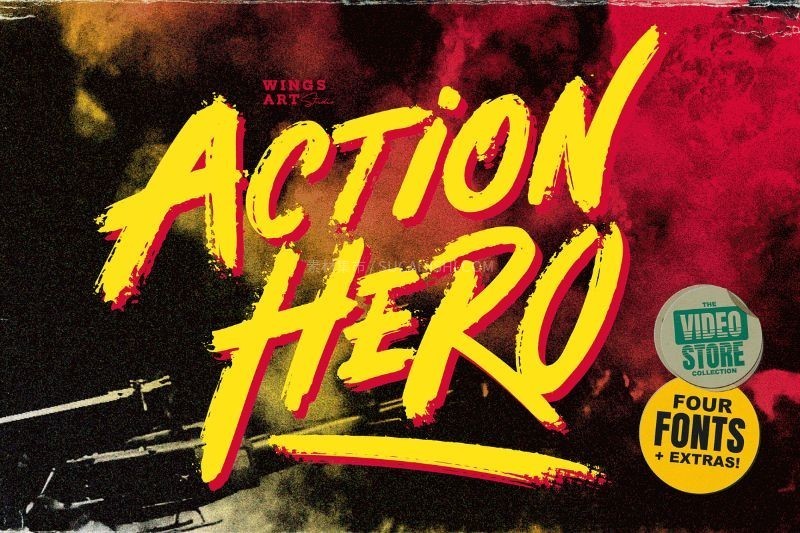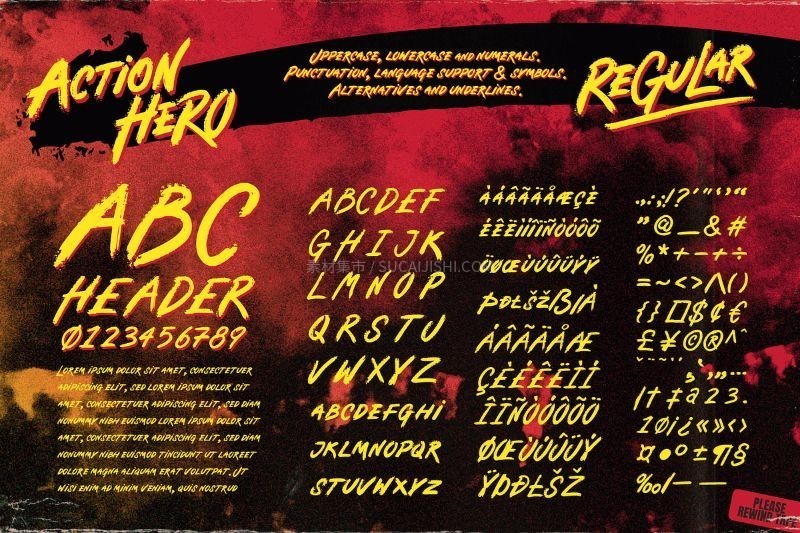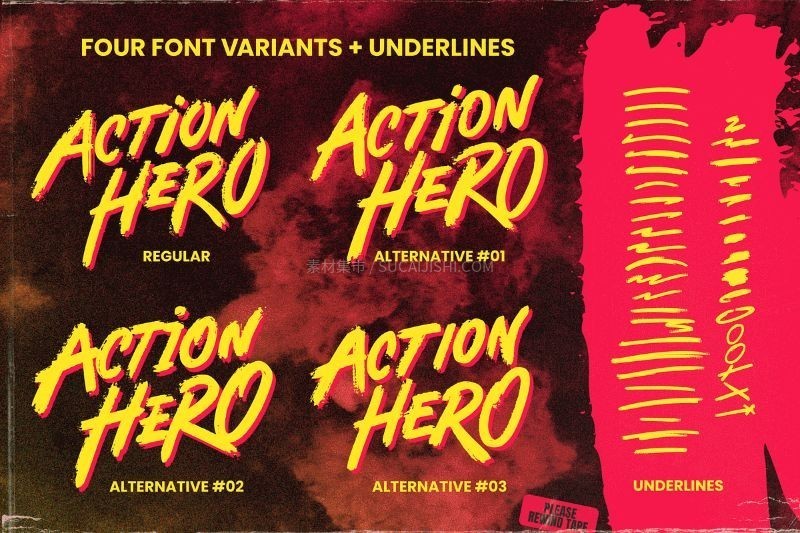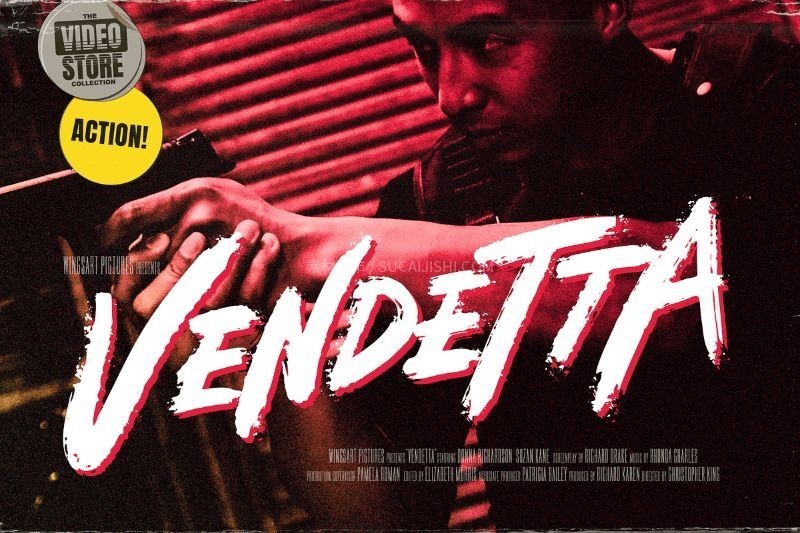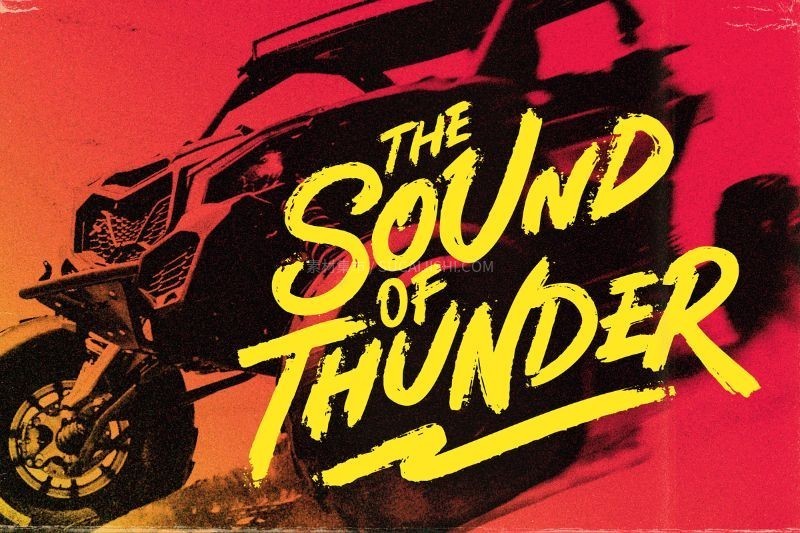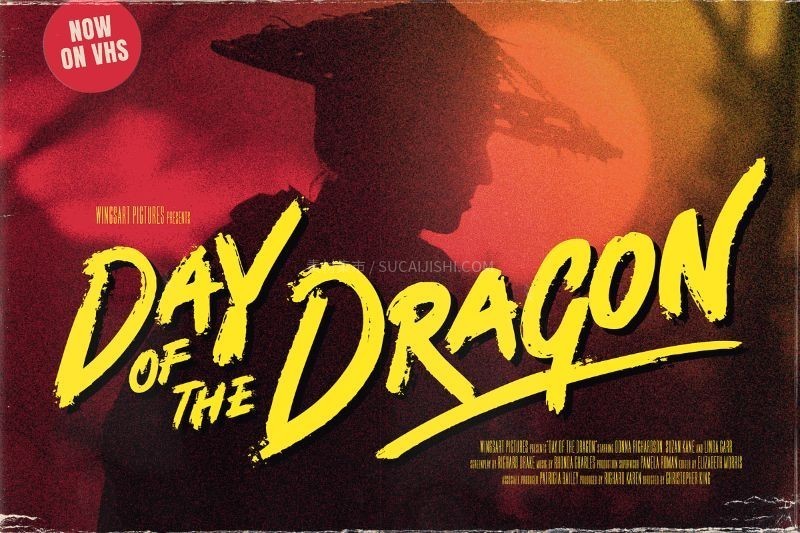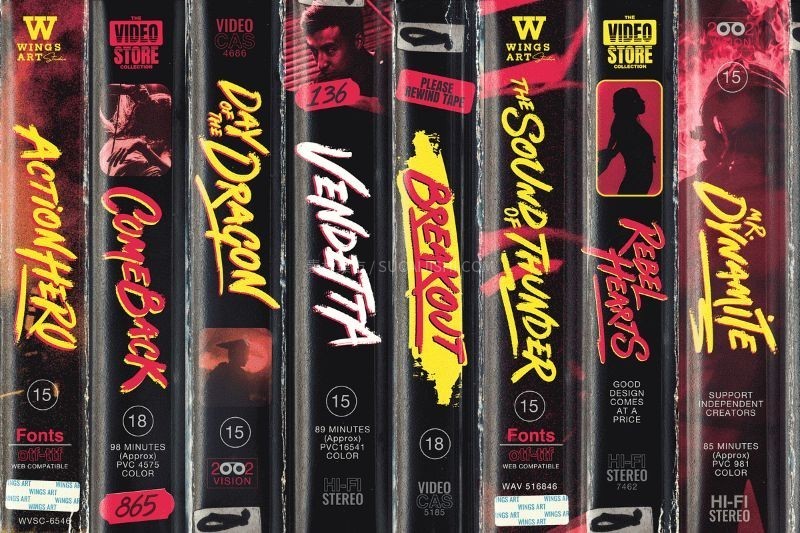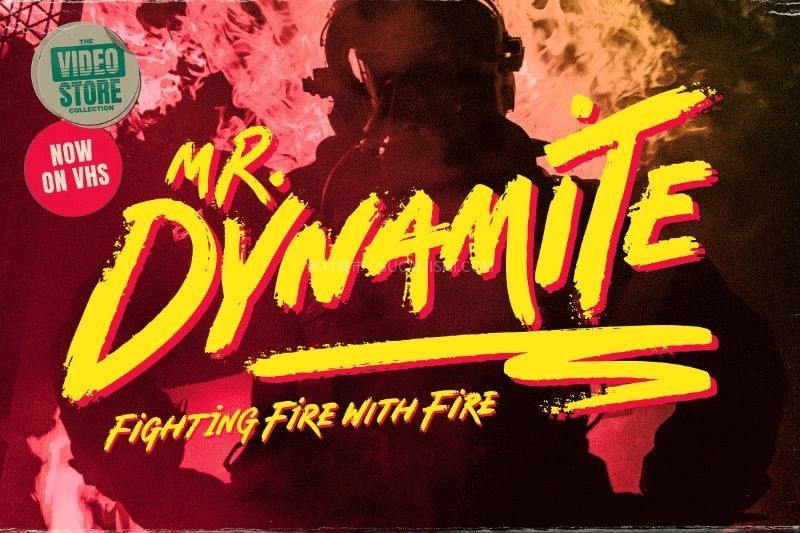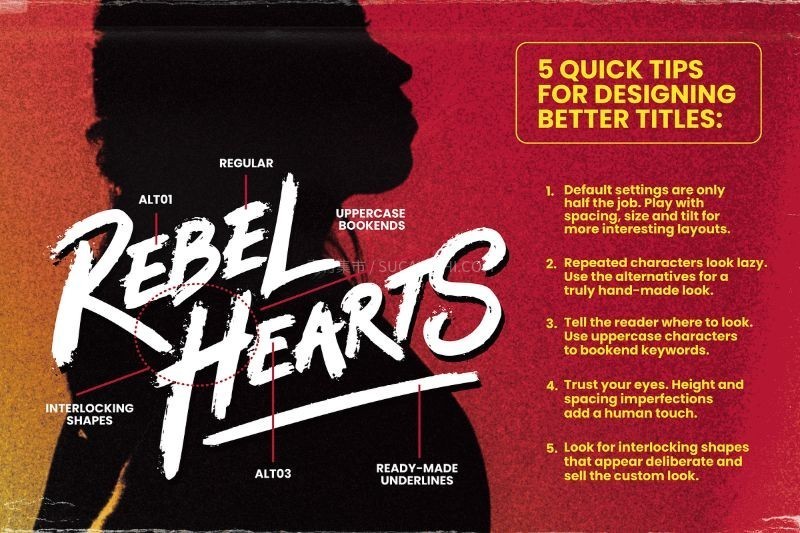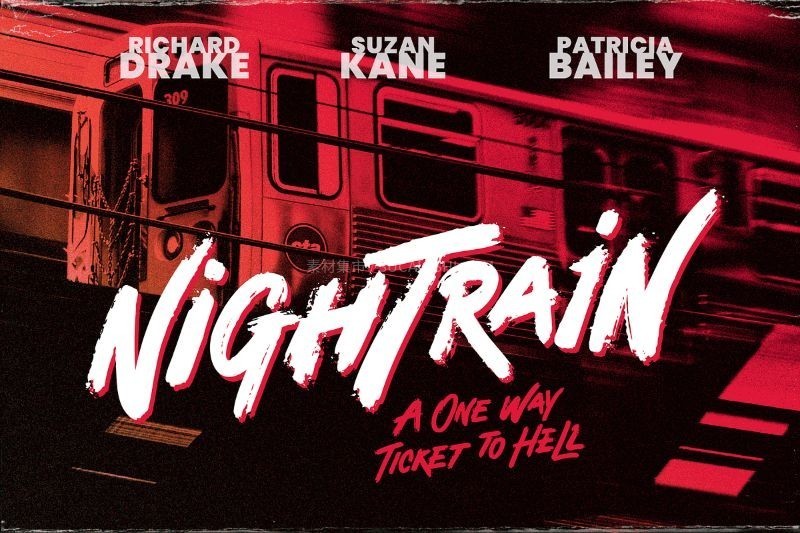
Action Hero 复古海报英文手刷字体
Action Hero 是一款致敬 80 年代和 90 年代经典动作片的手绘笔刷字体。它拥有粗犷的笔触和丰富的纹理细节,专为表现速度、力量与激情的场景而生。无论是疾驰的追车戏、孤胆英雄的营救任务,还是末日废土的狂野竞速,Action Hero 都能为您的画面注入肾上腺素。